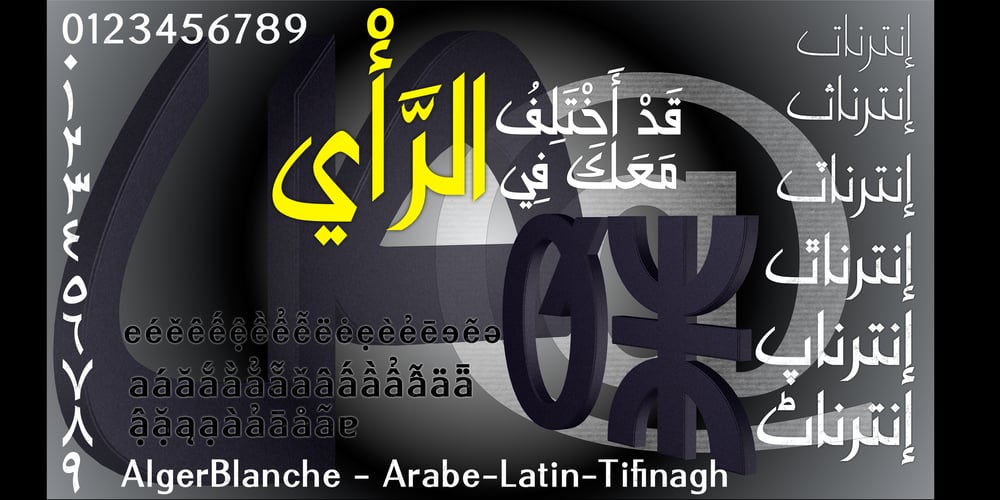
AlgerBlanche Font Family was designed by Ammar Bouras and published by GrafikarFonts. AlgerBlanche contains 5 styles and family package options. Alger Blanche est une police de caractère inspiré du koufi et naskh. AlgerBlanche supporte les scriptes. Arabe, Farsi, et OurdouDans cette mise à jour l’ajout du Latin et Tifinagh